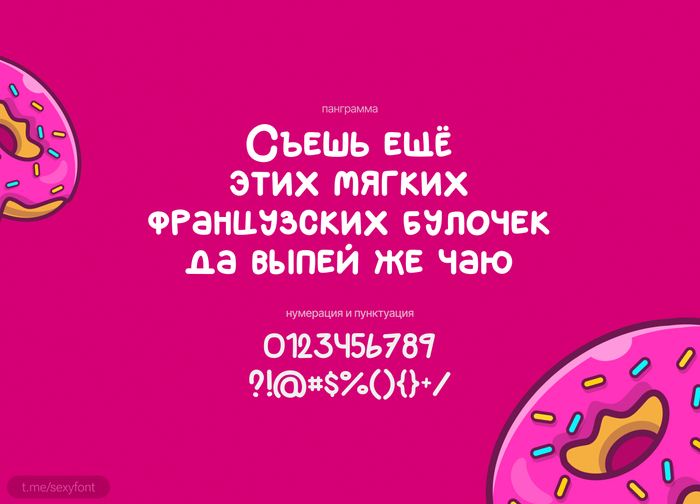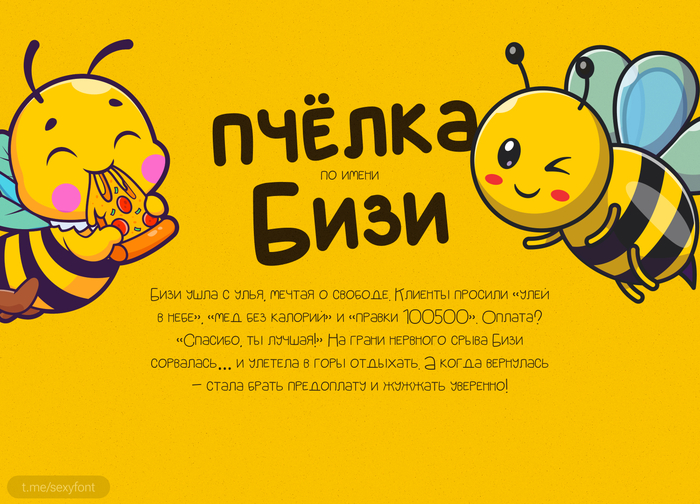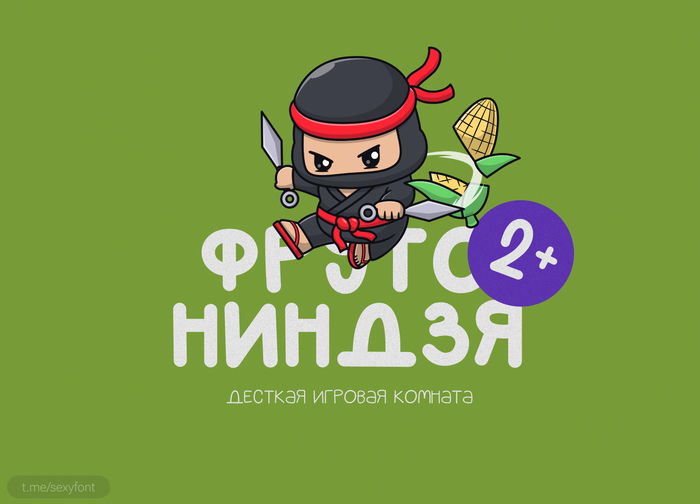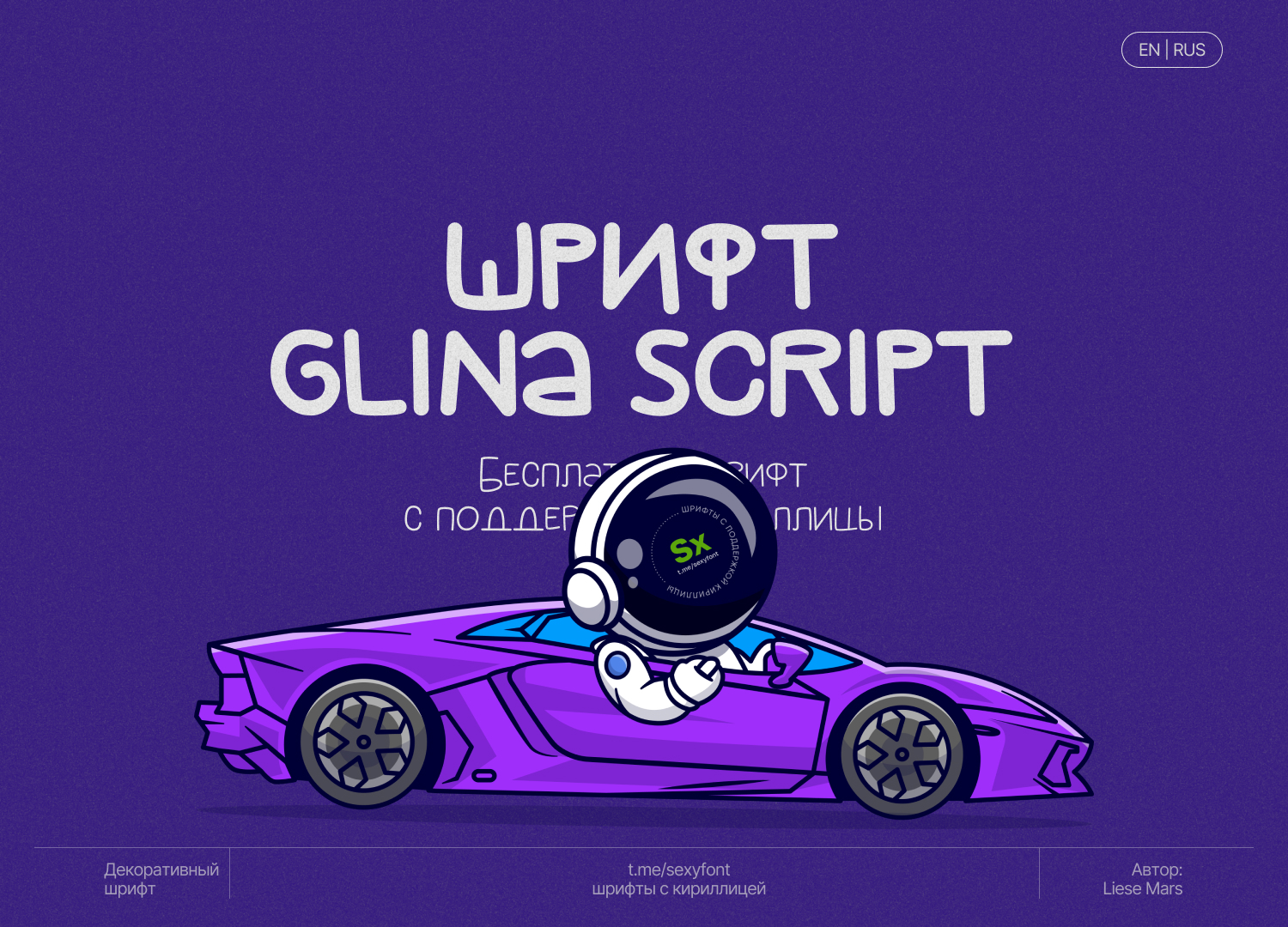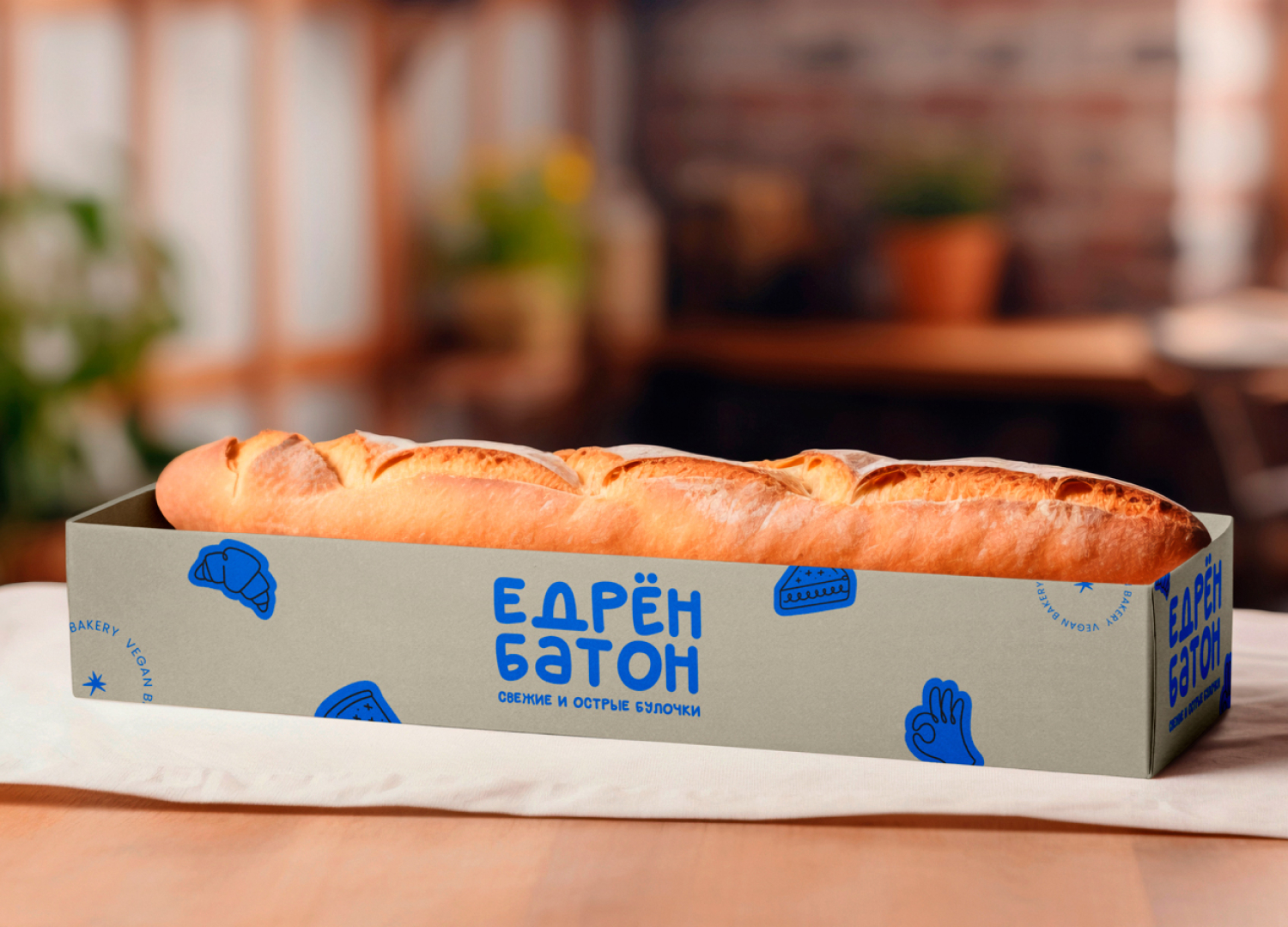
Шрифт Glina script
Glina script. Мягкий, плавный, веселый шрифтец. Конечно же с кириллицей и бесплатный для любого типа использования. Идеально для детских тематики или подписей к фотографиям.
Есть 2 начертания) В презентации показал